К истории немецкого шрифта — RusVerlag.de
Этот шрифт называется «немецким письмом», «готическим шрифтом» или «фрактурой». Шрифт, на котором пишутся немецкие книги сегодня, называется «антиква» или просто «латинский шрифт». Противостояние между «немецким письмом» и шрифтом «антиква» оставило немалый след в истории немецкого языка и Германии в целом. «Немецкое письмо» относится к так называемым «ломаным шрифтам», при котором начертание дуг, из которых состоит графическое изображения букв, прерываются в разных местах, и там, где при письме меняется направление пера, появляются излом. Противоположностью ломаным шрифтам являются «круглые шрифты», в которых при написании букв пишущий инструмент совершает округлые, изогнутые, дугообразные движения.
Другое название «немецкого письма» — «готический шрифт» — связано с готическим стилем в искусстве, возникшем в середине 12-го века. Основным нововведением этого стиля в архитектуре является «стрельчатая арка», пришедшая на смену «круглой арке» романского стиля.
Соответственно и появившиеся в то время шрифты, которые отличались изломами дуг, стали называться готическими.
Противостоящий «готике» круглый шрифт «антиква» появился в Италии в 15-м веке. Его появление связано с эпохой гуманизма и возросшим интересом к античности. При написании текстов итальянцы стали подражать начертанию букв в сохранившихся античных рукописях. Отсюда и название шрифта.
Первоначально и готические шрифты и «антиква» были рукописными шрифтами. С появлением книгопечатания возникли соответствующие печатные шрифты. Первые печатные книги в типографии Гутенберга были набраны одним из готических шрифтов — текстурой. Спустя короткое время в Италии появились печатные шрифты «антиква». В странах Южной Европы «антиква» относительно быстро вытеснила «ломаные шрифты». В странах Северной и Центральной Европы эти виды шрифта сосуществовали более длительное время. В большинстве стран «готические шрифты» исчезли к концу 18-го столетия, только в странах немецкого языка они сохранились до середины 20-го века.
Вначале применение того или иного шрифта не было идеологически обусловлено. Тексты на немецком языке с 16-го века печатались чаще всего одним из готических шрифтов — «фрактурой», тексты на латинском языке — «антиквой». На латинском языке издавались, наряду с античной классикой, также многочисленные научные труды.
Ситуация изменилась к началу 19-го века. Это был период подъема немецкого национального чувства, сопровождавшийся попытками определить, что «немецкое», а что нет, что характеризует «национальный дух» и культуру немцев, а что им чуждо. Мыслители того времени стали рассматривать шрифт «антиква» как ненемецкий, как воплощение таких чуждых немецкому духу свойств как легкость, несерьезность, поверхностность.
В то же время более темный и жирный шрифт «фрактура» воплощает в себе такие «исконно немецкие качества, как основательность, серьезность, глубина». Мать Гете писала своему сыну, чтобы он оставался немцем «и в буквах тоже». Тем не менее, в 19-м веке и в начале 20-го века все больше людей в Германии пользовались «антиквой», которую они считали более простым и удобным шрифтом.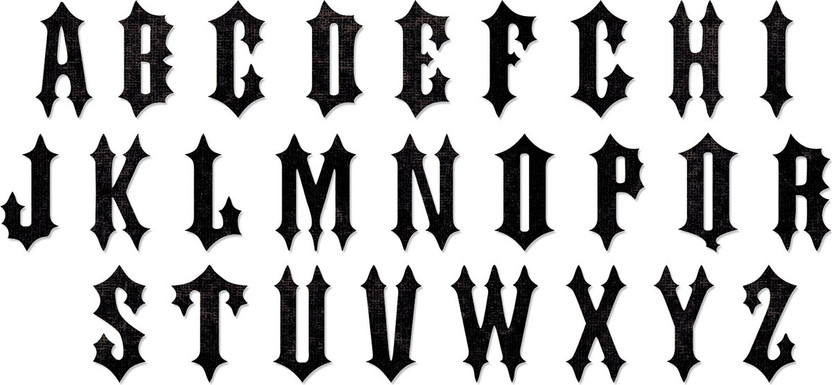
В начале 20-го века образовалось «общество сторонников старого шрифта» (Verein fuer Altschriftе), выступавшее за широкое распространение «антиквы». Название парадоксальное. Здесь понятия «старого» и «нового» как бы поменялись местами. Слово «антиква» в переводе с латинского означает старинный, древний. На самом же деле это общество выступало за модернизацию и упрощение шрифта.
В начале 20-го века шрифтом официальных документов оставалась «фрактура». В школах также обучали письму так называемым «немецким куррентшрифтом» — тоже одним из готических шрифтов.
В 1911 году Общество сторонников «антиквы» добилось рассмотрения в рейхстаге вопроса о замене фрактуры на латинский шрифт в официальном делопроизводстве и отмены обучения «немецкому куррентшрифту» в школах. В результате эмоциональных дебатов законопроект был отклонен 75 процентами голосов. Несмотря на это, «антиква» получала все большее распространение. Драматические события вокруг вопроса о шрифте развернулись в эпоху нацизма.
Вначале нацисты объявили, что только «ломаные шрифты» являются «истинно немецкими» и их использование всячески поощрялось. Ситуация резко изменилась в 1941-м году. 3 января 1941-го появился не предназначенный к публикации в открытой печати циркуляр Мартина Бормана, который неожиданно обвинил готический шрифт в еврейском происхождении и на этом основании запретил его. Интересно, что напечатан циркуляр был на бланке с надписями готическим шрифтом.
Циркуляр
(Не для обнародования)
Для всеобщей информации по поручению фюрера сообщаю:
Рассматривать так называемый «готический шрифт» как «немецкий шрифт» и употреблять по отношению к нему название «немецкое письмо» — неправильно. В действительности так называемый «готический шрифт» состоит из швабахских еврейских литер. Так же, как в более поздние времена евреи захватили газеты, так в период становления книгопечатания они взяли в свои руки типографии, результатом чего стало широкое распространение в Германии швабахских еврейских литер.
Сегодня фюрер после обсуждения вопроса с рейхсляйтером господином Аманном и владельцем типографии господином Адольфом Мюллером принял решение, что «антиква» — шрифт отныне должен именоваться «нормальным шрифтом». Постепенно вся печатная продукция должна быть переведена на «нормальный шрифт». Насколько это позволяет ситуация со школьными учебниками, в сельских и народных школах при обучении должен использоваться только «нормальный шрифт».
Наш инструмент — лучший генератор готического текста. Он преобразует ваш простой текст в причудливый текст в готическом стиле всего за несколько секунд, выполняя простые шаги копирования и вставки, что делает его популярным среди любителей готических шрифтов. Так что используйте бесплатный генератор готических шрифтов, не сталкиваясь с какими-либо проблемами. Наслаждайтесь шрифтами Goth
Готические шрифты — одни из моих любимых шрифтов, потому что у них много вариаций, и каждая из них более привлекательна, чем другая.